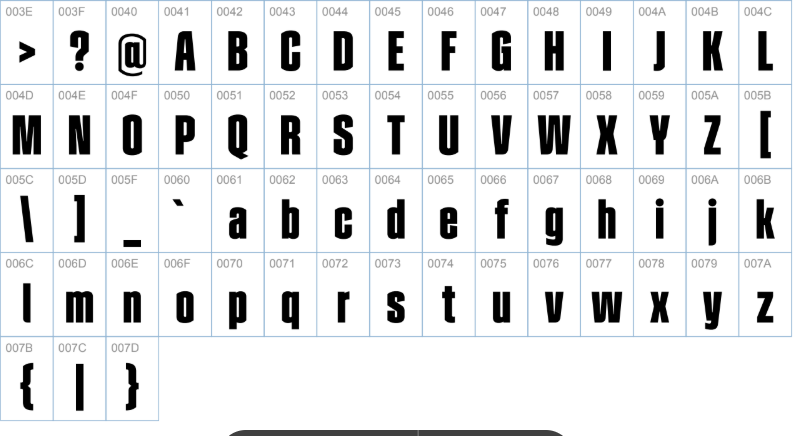
Mesmo nos momentos mais desafiadores, a torcida dos “Azuis Reais” (Die Königsblauen) nunca abandona o time. Para a temporada 2025-2026, a parceria histórica entre o clube de Gelsenkirchen e a Adidas entrega mais um uniforme que respeita a tradição mineira da região do Ruhr, mas com um acabamento visual extremamente moderno.
Se você busca precisão alemã para seus projetos, trazemos neste post a tipografia oficial que estampa o manto do Schalke 04 nas competições nacionais, pronta para download e uso imediato.
Estilo Visual e Aplicação
A identidade visual criada pela Adidas para o Schalke 04 nesta temporada reflete a robustez e a força industrial do clube. A fonte abandona curvas desnecessárias em favor de um design mais angulado e técnico, típicos da escola de design alemã.
Os números possuem cortes internos sutis que adicionam dinamismo sem comprometer a leitura, ideal para visualização rápida em campo. Esta tipografia é utilizada tanto no uniforme titular (o clássico azul royal) quanto no kit reserva e de goleiros, sendo perfeita para quem deseja criar mockups realistas ou personalizar camisas de torcida com o padrão original da Bundesliga.